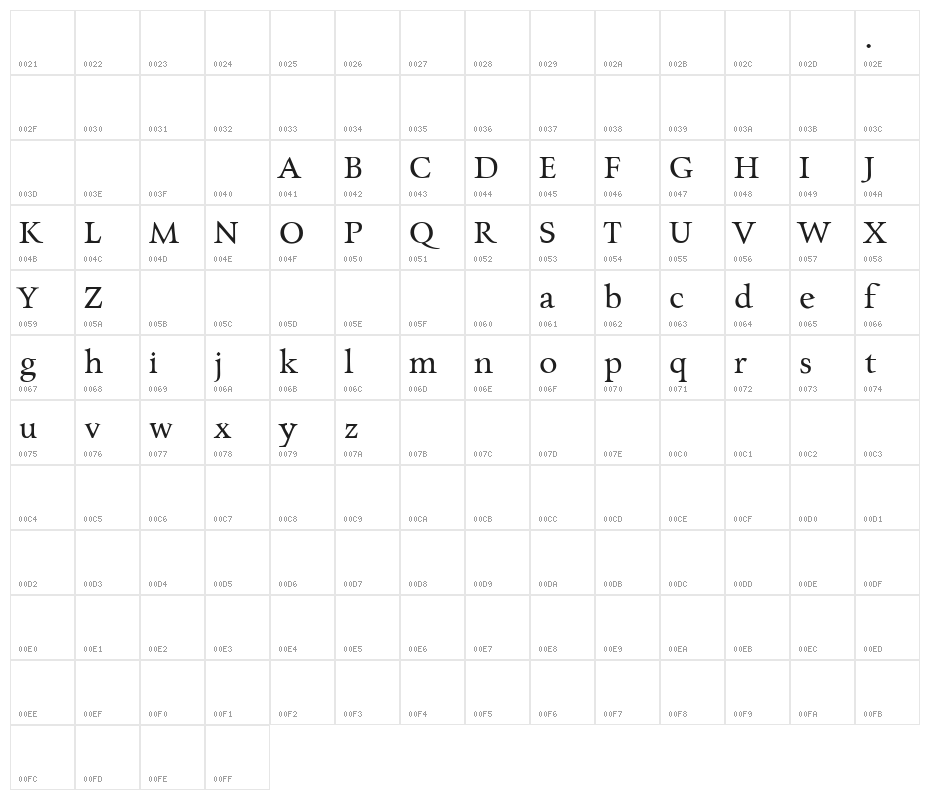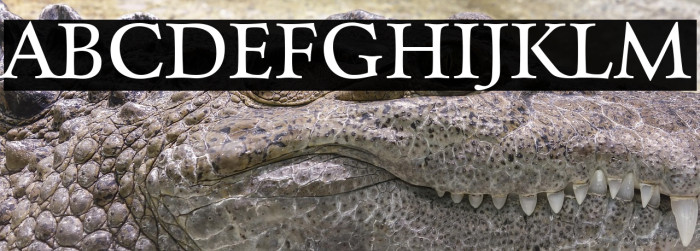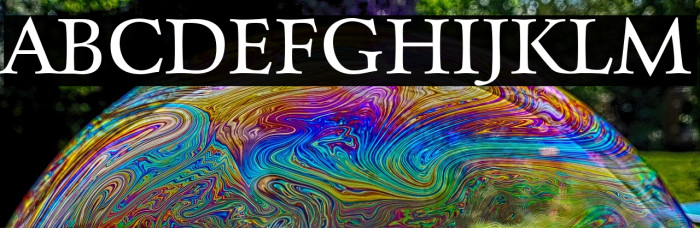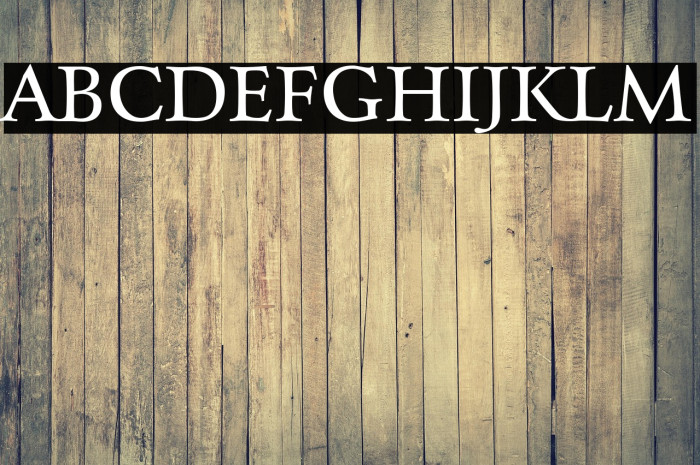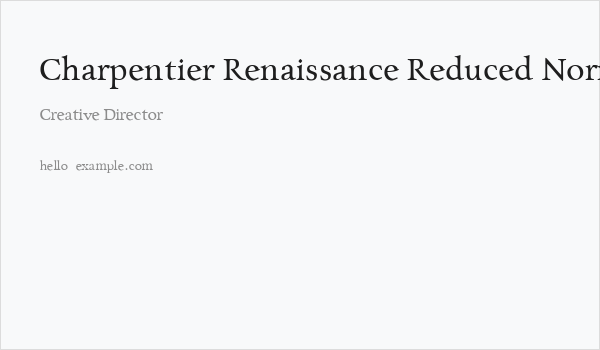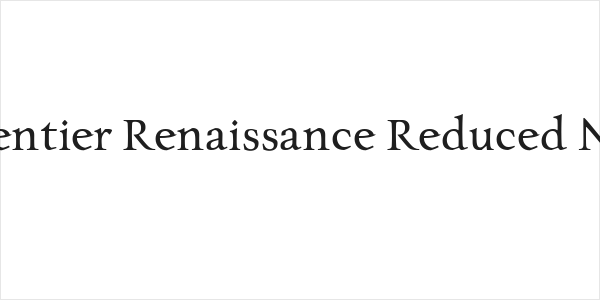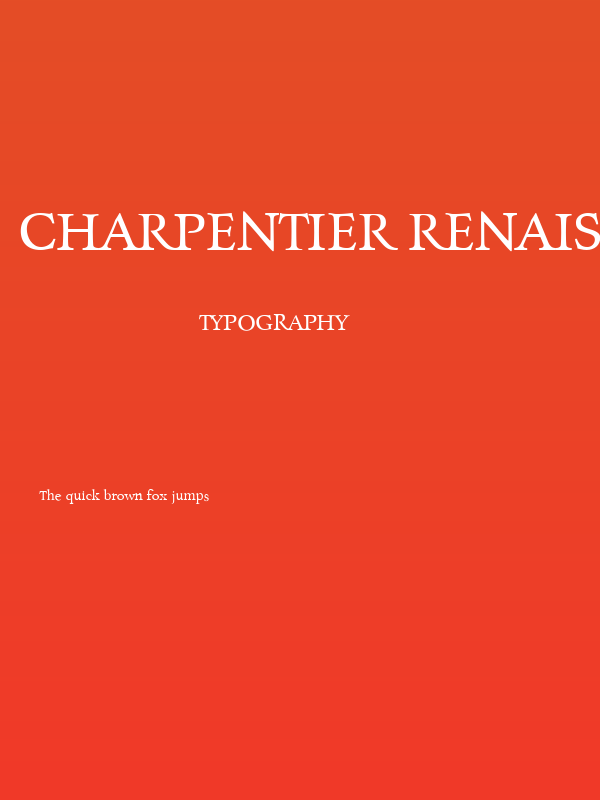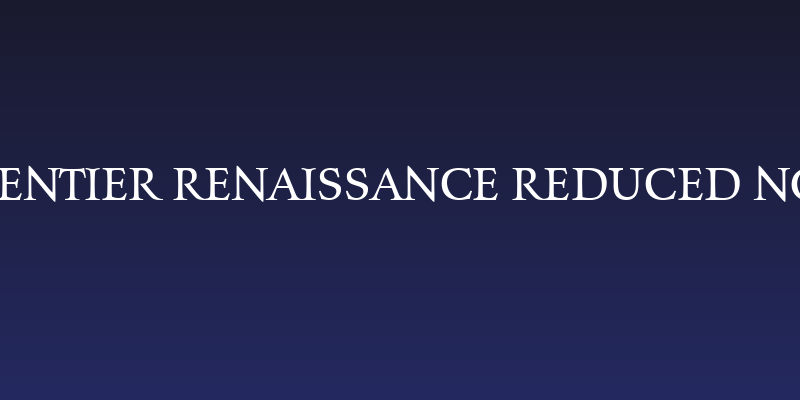
Charpentier Renaissance Reduced Normal Font
✎ Calligraphic
| 分类 | Calligraphic |
| 整体风格 | Classic |
| 使用场景 | Headlines, Body text, Logos |
| 推荐项目 | Ideal for use in historical documents, formal invitations, book titles, and branding that requires a touch of sophistication. |